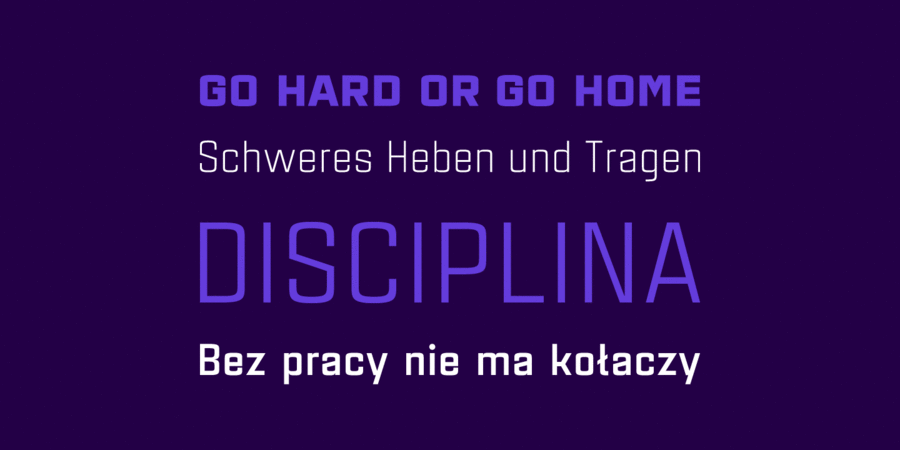
Опис гарнітури EstrictaЦе модульний гротеск з геометричним механічним зовнішнім виглядом, його гострі кутасті краї мають сильний та солідний характер. Шрифт був задуманий для коротких і середніх текстових блоків, а також для заголовків будь-якого розміру. Estricta складається з 12 накреслень. Кожне з них містить гліфи для багатьох мов на основі латинки й кирилиці, капітель та лігатури. Шрифт розробив Пабло Балселлс у 2017 році.
Особливості сімейства шрифтів EstrictaХіт десятиліття:
Хіт 1980-х Хіт 1990-х Estricta підтримує 83 мовиУкраїнська, Англійська, Німецька, Польська, Португальська, Іспанська, Французька, Російська, Чеська, Голландська, Італійська, Шведська, Турецька, Фінська, Білоруська, Сербська, Болгарська, Естонська, Литовська, Албанська, Африкаанс, Баскська, Бретонська, Валенсаска, Galician, Гельська (Шотландська), Данська, Індонезійська, Ірландська, Ісландська (Win), Каракалпацька, Каталонська, Норвезька, Окситанська, Ретороманська, Самі Лулі, Тсванська, Узбецька (Лат.), Фарерська, фризька, Чаморро, Естонська (Win), Південносаамська, Албанська (Win), Угорська, Верхньолужицька, Карельська, Латвійська (Mac), Литовська (Mac), Маорійські (Mac), Молдавська (Лат.), Нижньолужицька, Румунська (Win), Словацька, Словенська, Туркменська (Лат.), Хорватська (Win), Естонська (Mac), Курдська, Латишська, Маорійські, Руминська, Абазинська, Аварська, Агульська, Адигейська, Даргинську, Інгуську, Кабардино-Черкеська, Кабардинська, Карачаєво-Балкарська, Кумицька, Лакська, Лезгинська, Македонську, Мордовсько-Мокшанська, Мордовсько-Ерзянська, Ногайська, Рутульська, Табасаранська, Татська, Цахурська, Чеченська Функції сімейства шрифтів EstrictaЗастосування гарнітури у верстці:
Асоціації з сімейством шрифтів EstrictaОсобистість і характер гарнітури:
неоновий, точний, футуристичний, рівний, прямокутний, тонкий, статичний, логічний, холодний, легкий, міський, сучасний, інженерний, урбаністичний, креслярський, скляний, крихкий, прозорий, спокійний, дротяний, худий, чіткий, різкий, гострий, стійкий, космічний, машинний, стабільний, твердий, серйозний, техногенний, практичний, прагматичний, технічний, якісний, міцний, надійний, формальний, впевнений, архітектурний, переконливий, сильний, індустріальний, крутий, амбітний, авторитетний, мотивуючий, автоматичний, сталевий, діловий, монотонний, штучний, важливий, військовий, залізний, робочий, відповідальний, жорсткий, суворий, важкий, гучний, гарячий, монументальний
фантастика, гаджет, девайс, креслення, архітектура, інженер, Місто, електроніка, прилад, наука, айтішник, айті, IT, технології, космос, дизайн, техніка, конструктор, автоматика, астрономія, гра, авто, шутер, екшен, урбаністика, рентген, комп'ютерна гра, промисловість, верстат, інструмент, електростанція, енергетика, завод, тренажери, ремонт, блокбастер, бойовик, ракета, супутник, армія, зброя, машинобудування, порт, страйкбол, будівництво, вантажівка, далекобійник, сталевар, мотор, двигун, вагон, залізниця, робот, Футбол, спорт, робочий, селфі, кінотеатр, паливо, кіно, нафта Гарнітура асоціюється з віком: